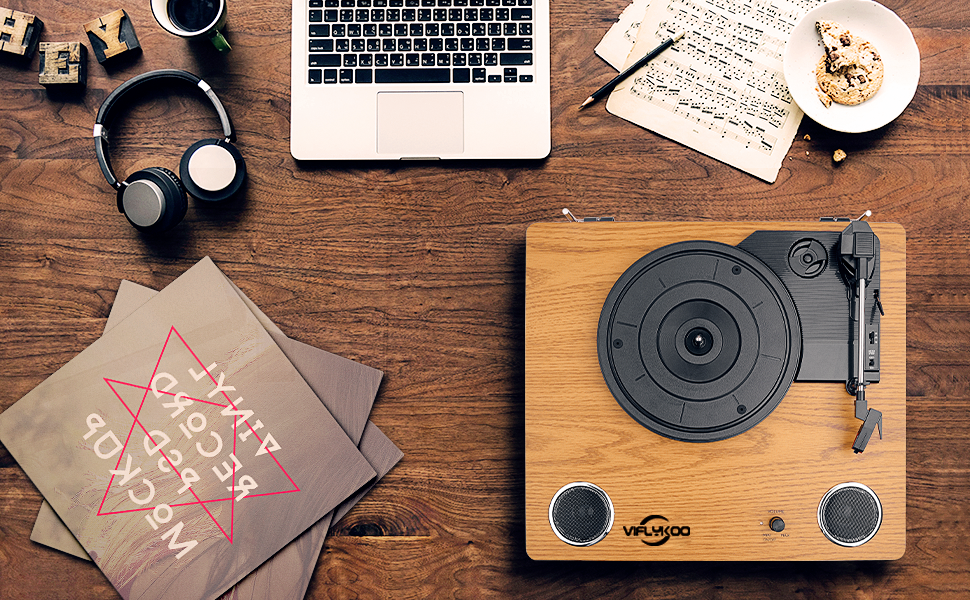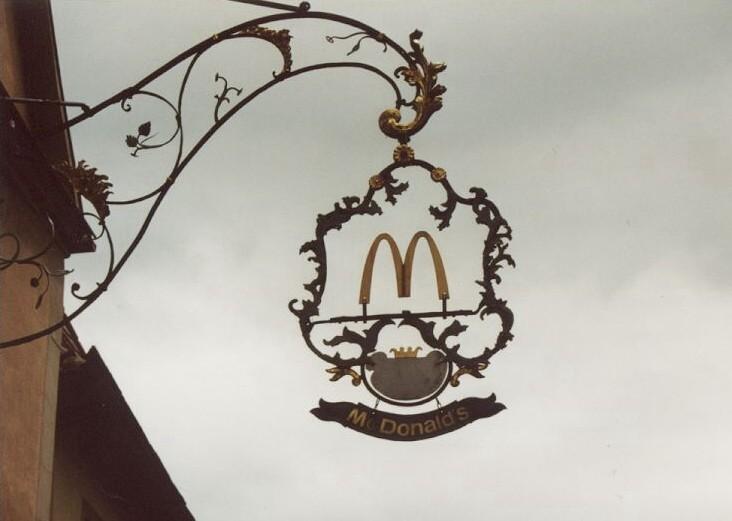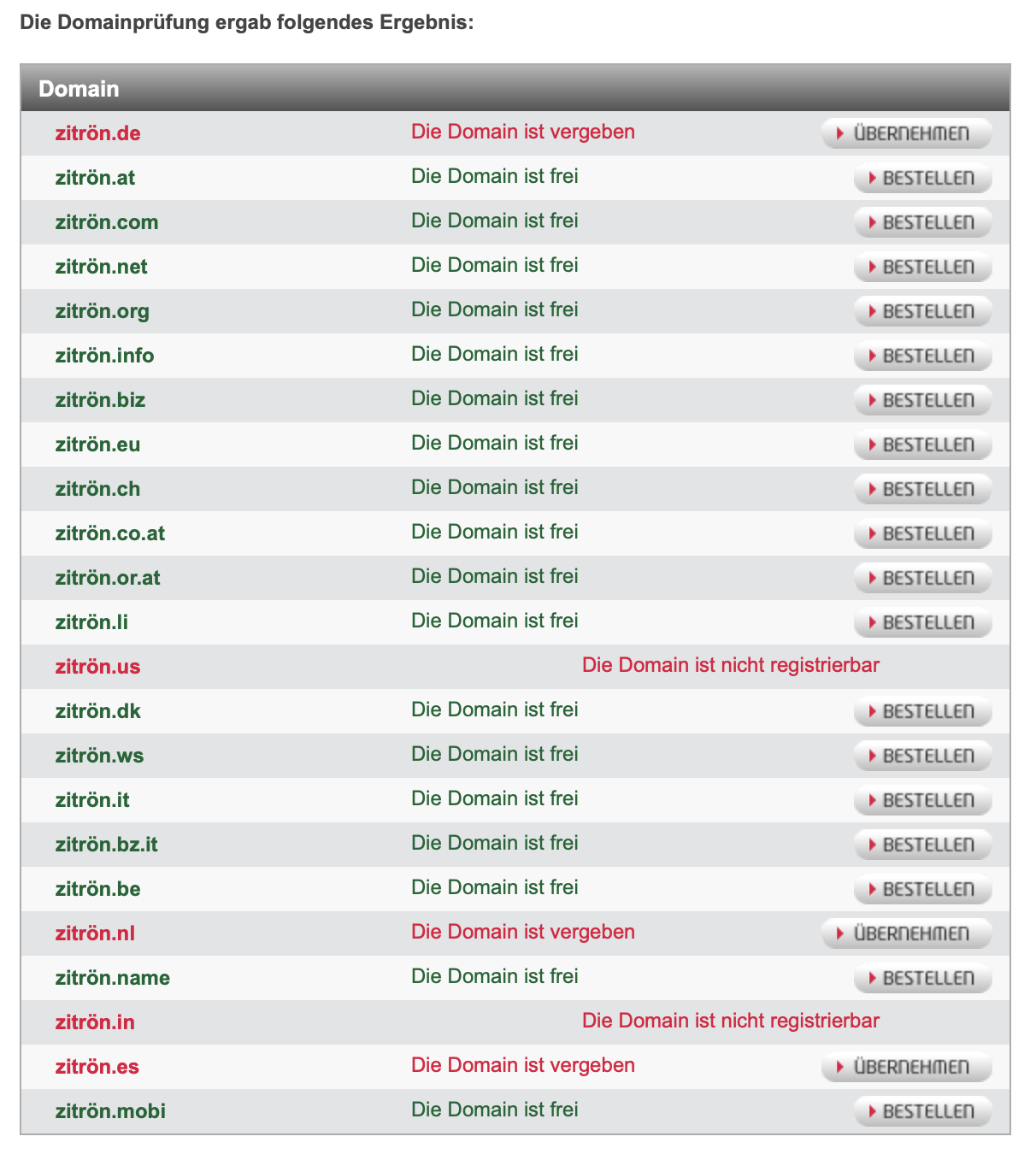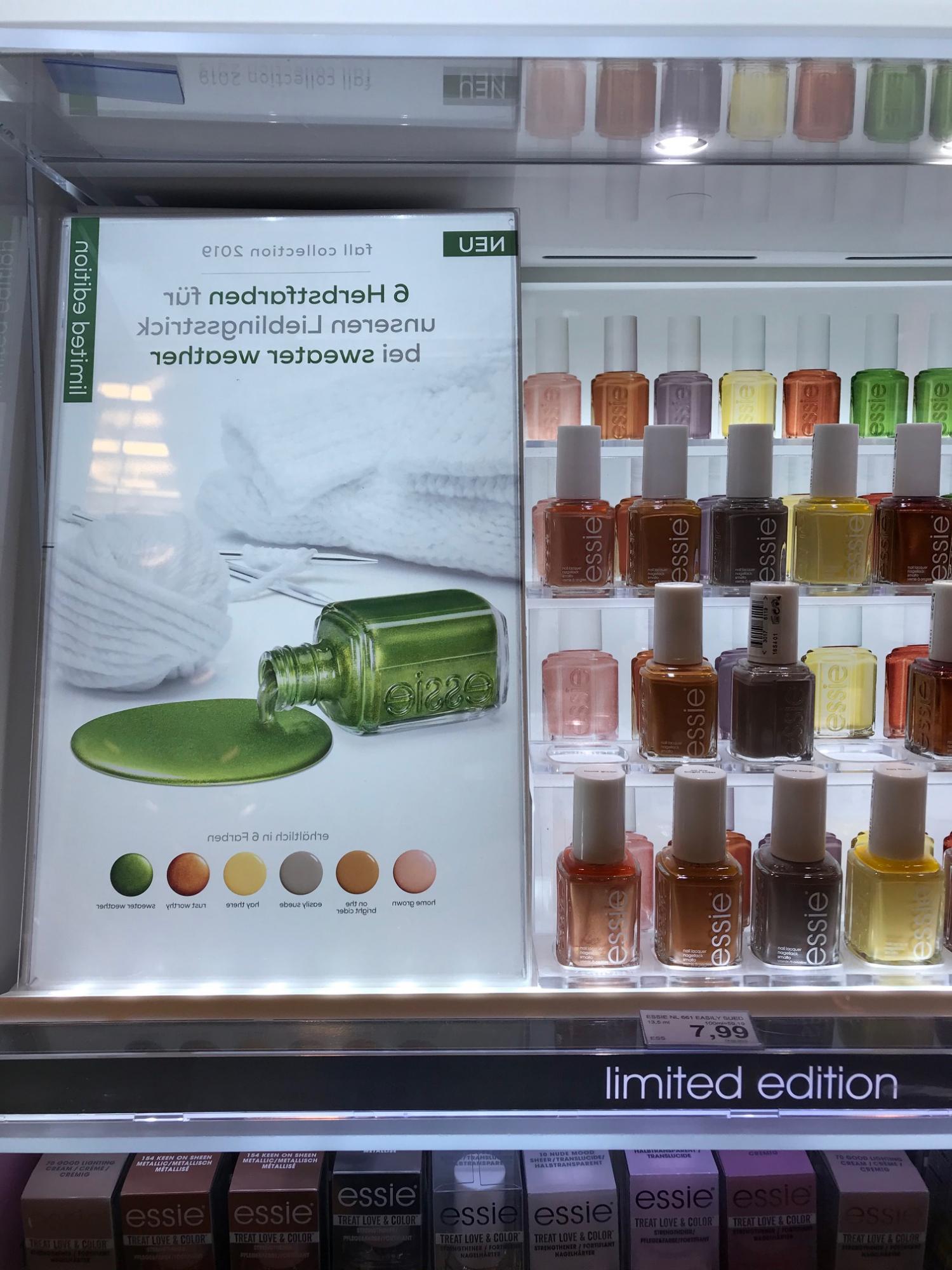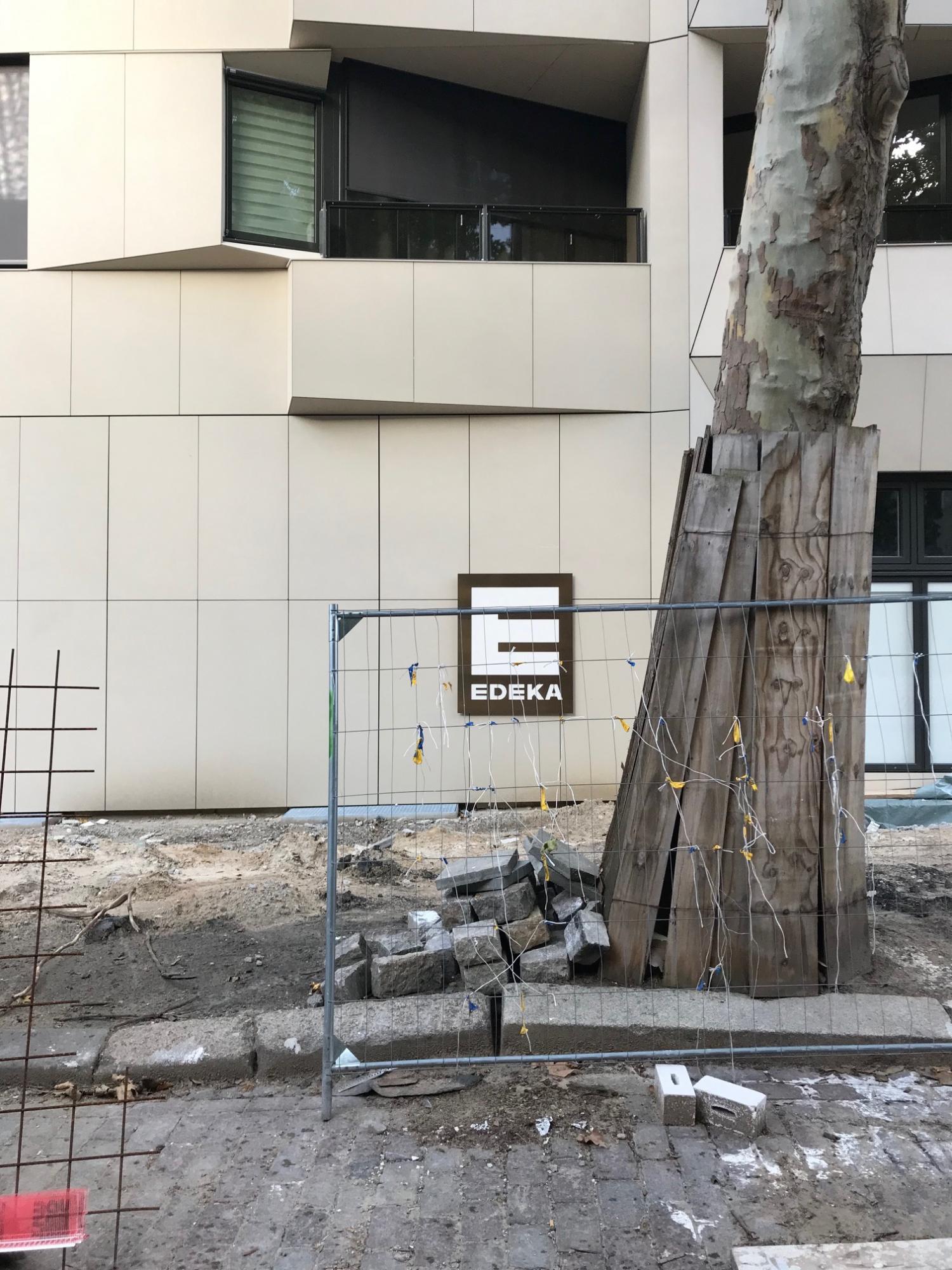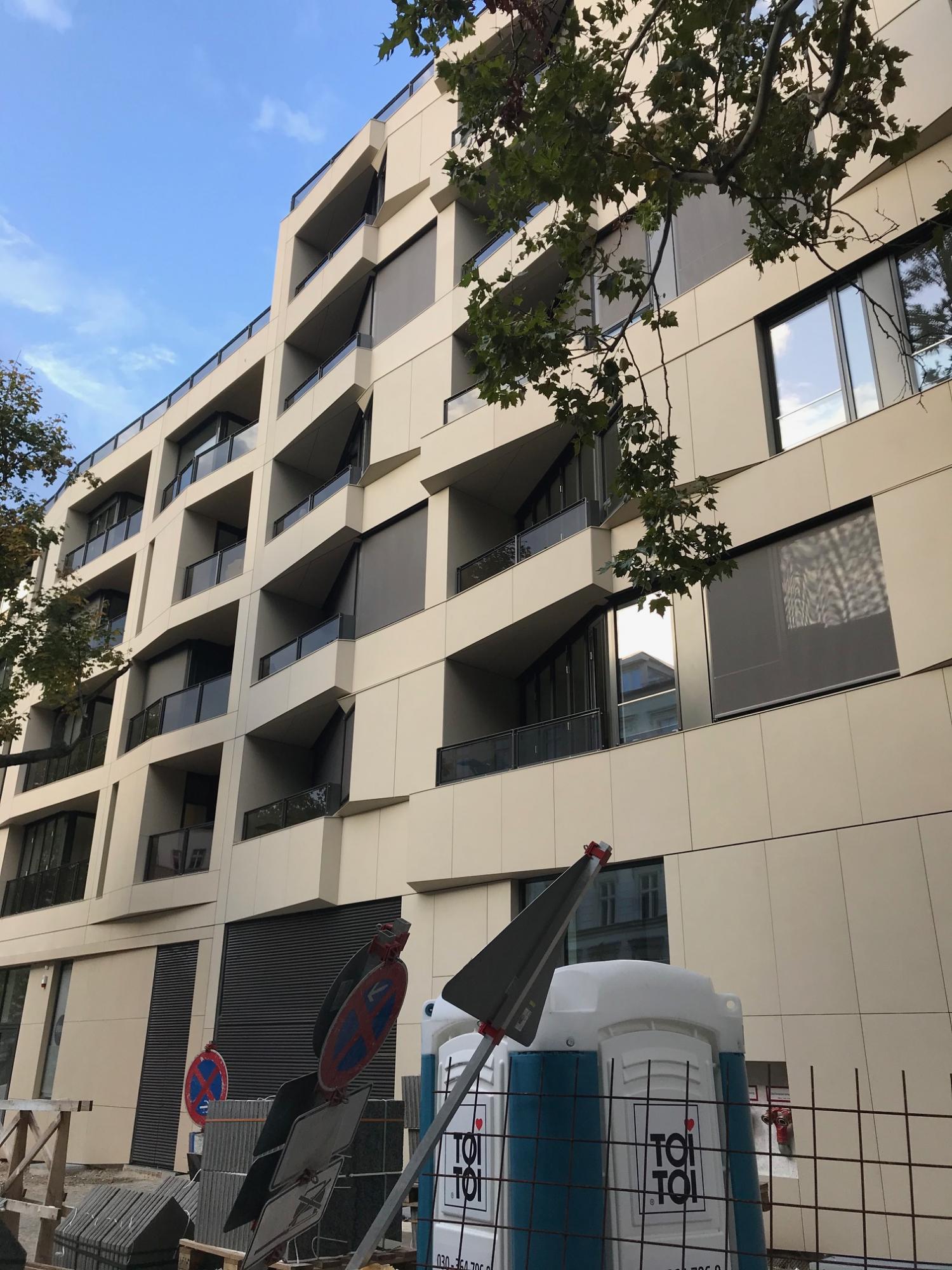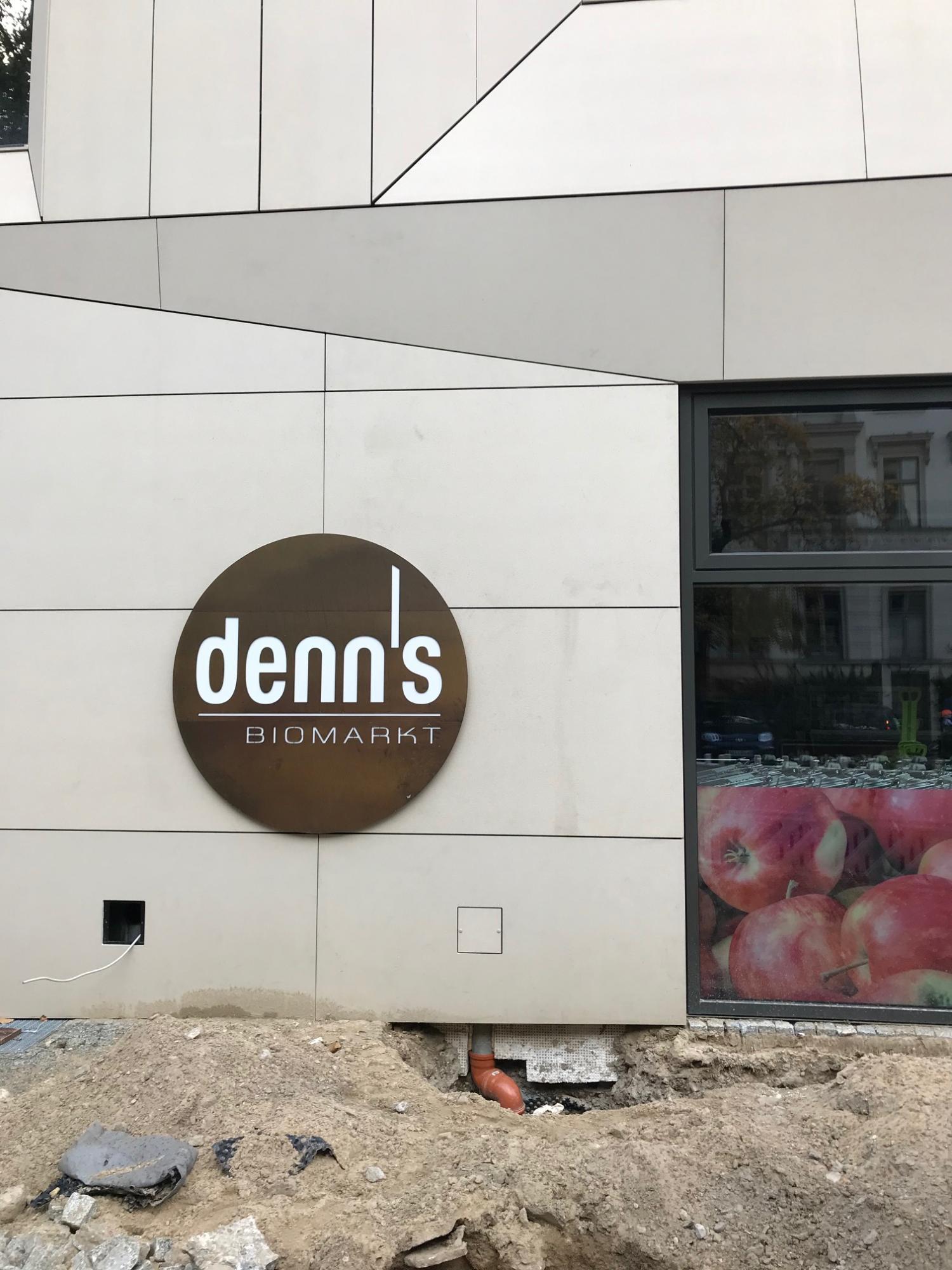
Kann eigentlich die Umlautdomaintechnik das Versal-Eszett?
Nicht so wirklich. Zum einen scheinen die meisten Browser ẞ in SS bzw. ss zu übersetzen, bevor überhaupt irgendein Server gefragt wird. Zum anderen scheint es schwierig bis unmöglich zu sein, unter den meisten TLDs Domains mit ẞ zu registrieren. Und dann liefert die DENIC dann über whois auch noch folgendes:
Anscheinend gibt es eine Regel, die (zumindest in .DE) nur erlaubt, Domains mit Buchstaben zu registrieren, für die immer A → a → A gilt, also die Groß-/Kleinbuchstabenumwandlung umkehrbar ist.
P.S. Und ich vermute mal, dass sich das auch nicht ändern wird, bis webrelevante Standards wie ECMAScript folgendes spezifizieren und die Browser das auch implementieren:
'ß'.toUpperCase() == 'ẞ'
'ẞ'.toLowerCase() == 'ß'
Das gibt’s öfter mal, meist aber bei denkmalgeschützten Altstädten …
Das gibt’s öfter mal
Hier 🇺‍🇸 auch, auch bei neuen Strip Malls oder, wie im Bild, innerstädtischen Projekten.
Hier mussten sich die Logos der Architektur unterordnen - zumindest farblich. 8-)
Skandal! Die Äpfel sind weiterhin rot!
Das hab ich beim betrachten des Bildes auch gedacht ... Kiwis hätten farblich besser gepasst.
Skandal! Die Äpfel sind weiterhin rot!
Gib denen 14 Tage Sonneinstrahlung, dann sind die hübsch entsättigt ;-)
Ja, wenn man die Äpfel erst nach 30 Tagen in der Sonne liegend geknippst hätte, wären sie fast alle schön kiwifarben ... Jedenfalls außen, innen weniger ...;-)
War gerade auf der Suche nach einem Plattenspieler und bin auf diesen hier gestoßen:
Keine Panik, der hat’s nicht in die engere Auswahl geschafft, aber dass Bild wollte ich euch nicht vorenthalten :nicken:. MacBook und Plattenspieler sind richtig rum, aber das Vinyl-Mockup (:oops:) und die lustigen Holzbuchstaben sind gespiegelt – letztere kann man daher wenigstens lesen :hammer:
Edit: Stimmt, eigentlich ist nur die LP gespiegelt
Das ist ja auch die limited edition …